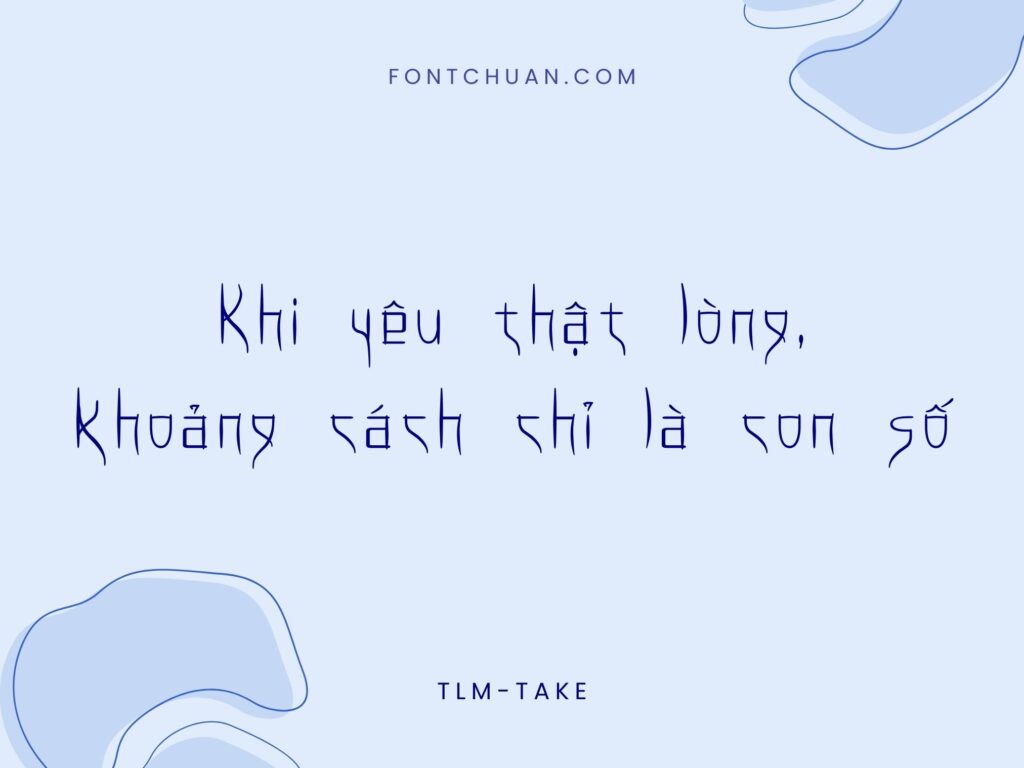
Font Take Regular Việt Hóa
TLM-Take là một font chữ mang phong cách cổ trang, được thiết kế lấy cảm hứng từ chữ viết tay với các nét và dấu mang phong cách Trung Hoa. Font này phù hợp với các thiết kế cổ trang, bìa sách, bìa truyện, thiệp mời và các dự án thiết kế khác. Phiên bản Việt hóa được thực hiện bởi cộng đồng, hỗ trợ đầy đủ tiếng Việt và nhiều ngôn ngữ khác. Font được sưu tầm và đăng bởi thành viên của Font Chuẩn.
Font có thiết kế với các ký tự thường và ký tự in hoa, cho phép kết hợp để tạo ra các tác phẩm độc đáo. TLM-Take phù hợp cho các thiết kế liên quan đến thương hiệu, tiêu đề, poster và các ấn phẩm truyền thông cần sự khác biệt và ấn tượng. Các ngành nghề như quảng cáo, thiệp cưới, giáo dục và ẩm thực có thể tận dụng hiệu quả font này. Ngoài ra, TLM-Take cũng thích hợp cho các sự kiện như lễ hội, sinh nhật, ngày Nhà giáo và Valentine, đôi khi cũng được dùng như Font chữ Halloween.